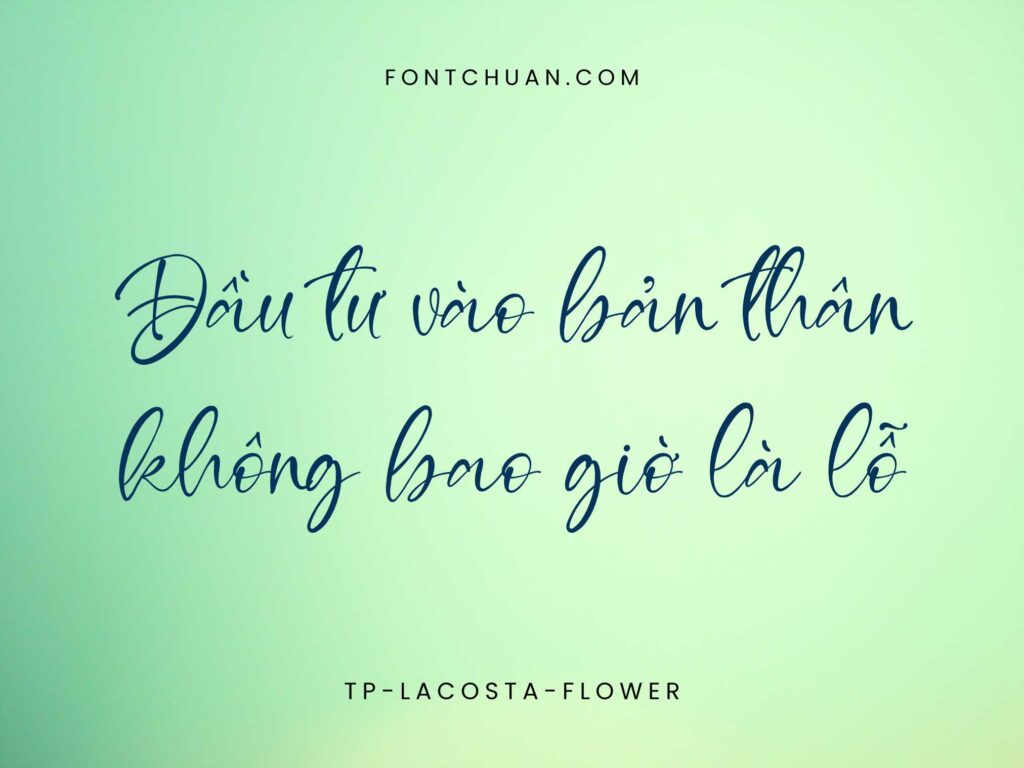
Font TP Lacosta Flower Việt Hóa
Tác giả Font: Create Big Supply
Lacosta Flower là một font chữ viết tay thanh lịch, mang lại cảm giác tự nhiên và tinh tế cho các thiết kế của bạn. Font này được thiết kế bởi Create Big Supply và phát hành trên Creative Fabrica. Với các ký tự mềm mại và uyển chuyển, Lacosta Flower phù hợp cho các dự án như thiệp mời đám cưới, thiệp chúc mừng, logo và các dự án thương hiệu cần sự cá nhân hóa. Font đã được Việt hóa để hỗ trợ tiếng Việt bởi Tuỳn Pucca, giúp người dùng Việt Nam dễ dàng sử dụng trong các dự án thiết kế. Font này được sưu tầm và chia sẻ bởi thành viên của Font Chuẩn, đáp ứng nhu cầu sử dụng đa dạng trong cộng đồng thiết kế.
Đặc điểm thiết kế của Lacosta Flower bao gồm các nét chữ mượt mà và tự nhiên, tạo cảm giác gần gũi và thân thiện. Font này phù hợp cho các ứng dụng như thiệp mời, logo, thương hiệu cá nhân và các dự án sáng tạo khác. Các ngành nghề phù hợp bao gồm quảng cáo, nghệ thuật và thiết kế đồ họa.